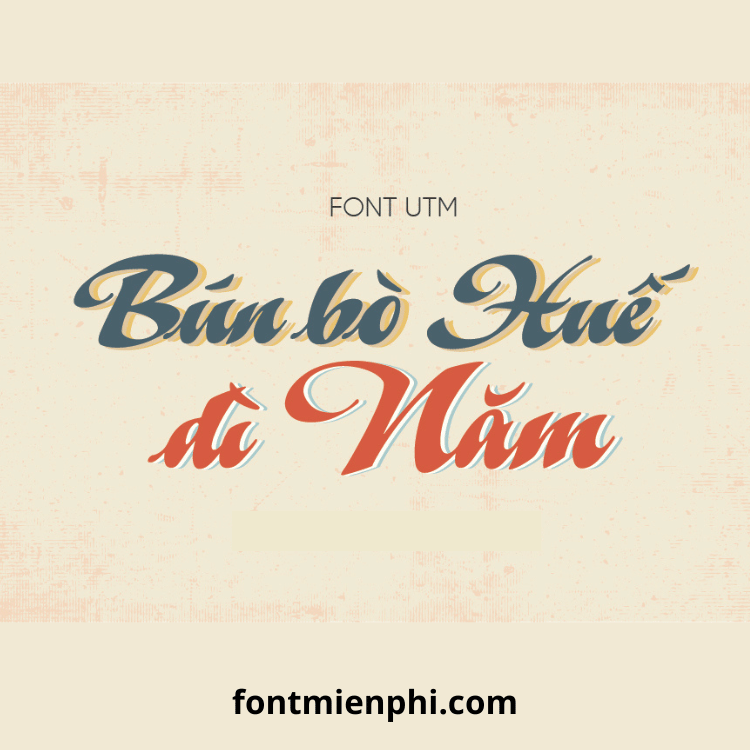
Font việt hóa UTM A&S Graceland
Font UTM A&S Graceland là một trong những font chữ đẹp, sang trọng, phù hợp cho thiết kế logo, banner, in ấn và nhiều dự án sáng tạo khác. Bản Việt hóa của font này giúp người dùng tại Việt Nam dễ dàng sử dụng với đầy đủ dấu tiếng Việt, mang lại trải nghiệm thiết kế mượt mà và chuyên nghiệp.
Đặc điểm nổi bật của Font UTM A&S Graceland Việt Hóa
✔ Hỗ trợ đầy đủ tiếng Việt – Font được Việt hóa chuẩn, đảm bảo hiển thị rõ ràng các ký tự có dấu.
✔ Phong cách sang trọng, hiện đại – Phù hợp cho thiết kế thời trang, logo, tạp chí, quảng cáo.
Kết Luận